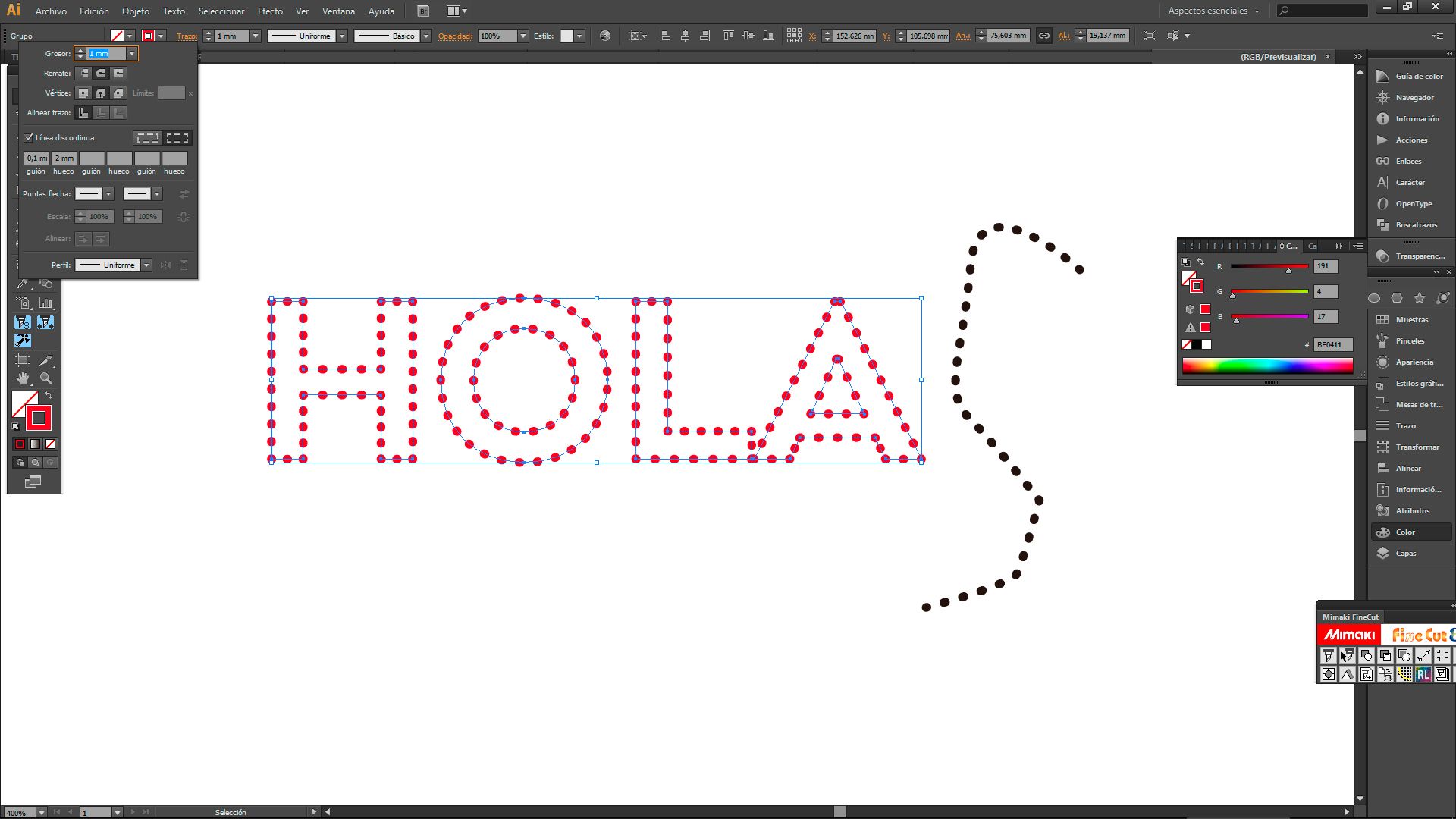
Illustrator tipografía puntos.
Buenas a tod@s!! ¿Alguien sabe como hacer en illustrator texto en puntos, sin ser una tipografía en concreto?
Ejemplo en la bolsa de esta web.
La opción buena es la que dice @cristianblan pero en vez de dibujar las letras, escribe con la tipo que quieras y "Crea contornos" así tendrás las letras dibujadas más rapido y mejor...
Luego el resto lo haces como te dice él.
Dibujas el texto en lineas con la herramienta pluma, luego entras al "panel trazos" en ilustrator y seleccionas la opción linea discontinua, seleccionas, extremos redondos...y unión redondeada..., luego encuentras el punto justo entre grozor de trazo, guión y hueco...y yasta..